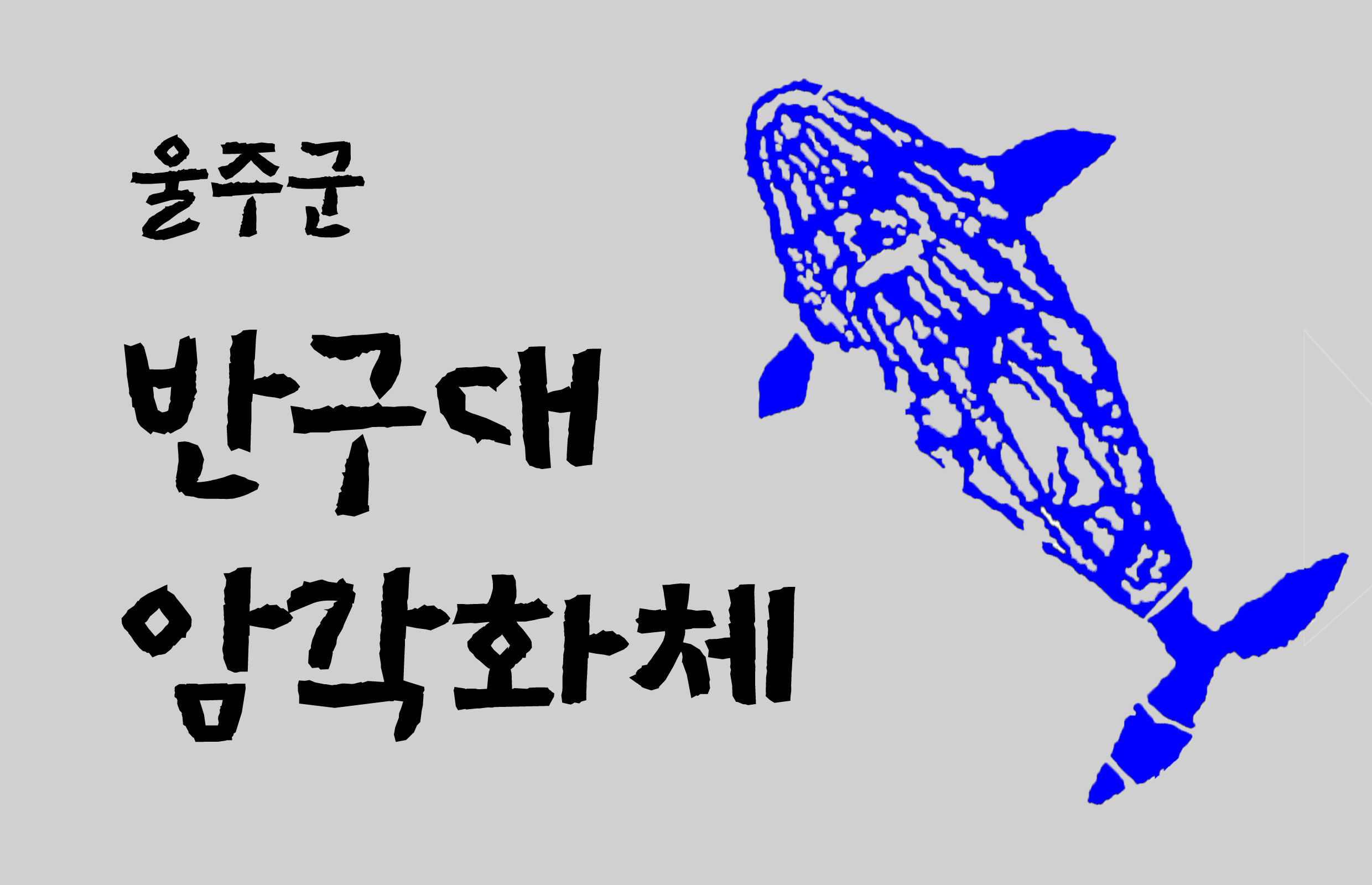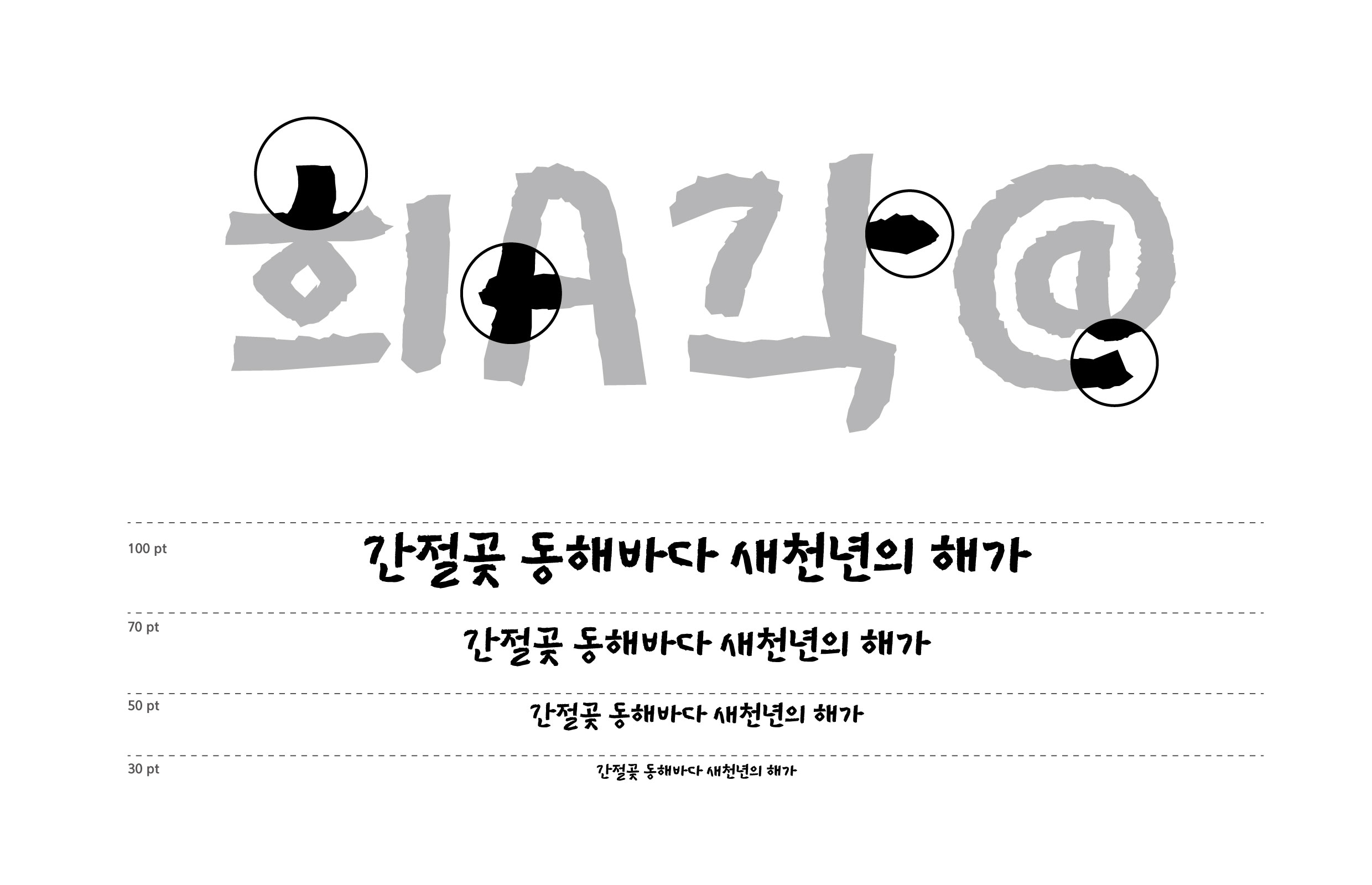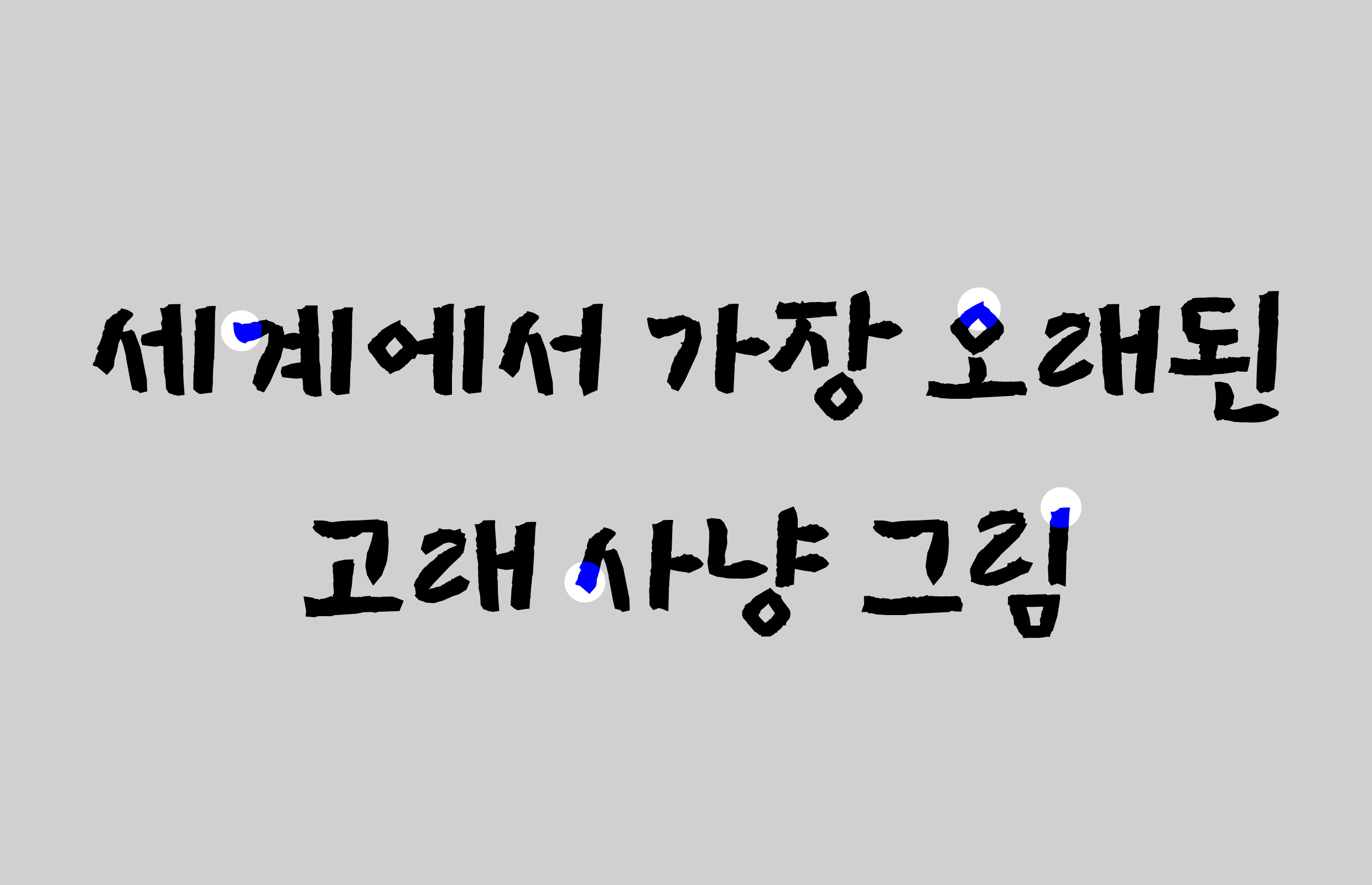
울주군 [반구대암각화체]
울산 울주군 반구대 암각화 발견 50주년을 맞이해 대곡천 암각화군 서체 2종을 제작했다. 반구대 암각화체는 바위 전각의 특징을 최대한 살린 캘리그라피 서체로, 천전리 각석체는 천전리 각석에 새겨진 기하학적 도형의 모습을 살린 현대화된 서체로 구현되었다.